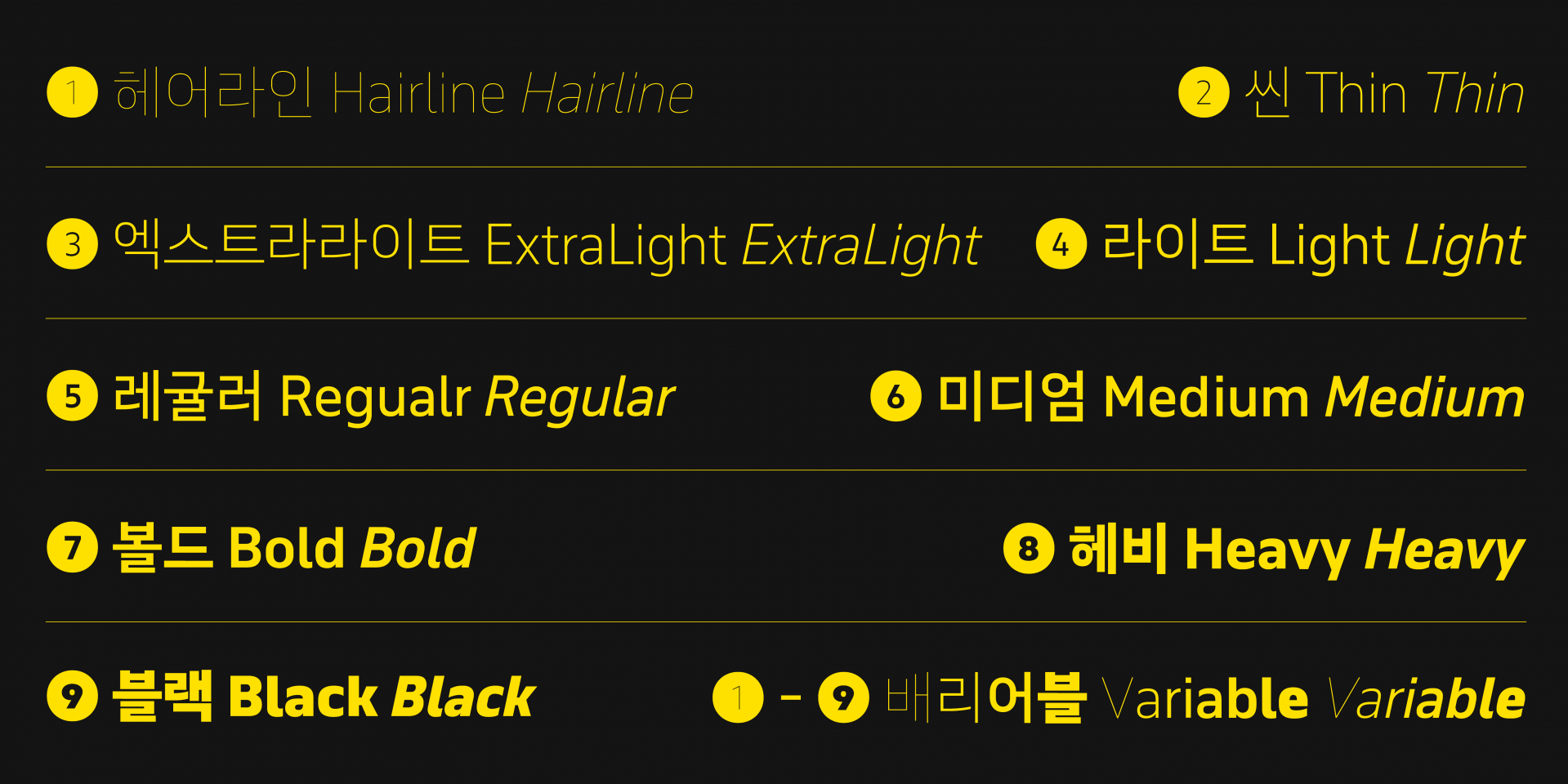
[Making font]세계 270곳에서 유창하게 대화할 수 있는 대가족
만나서 반갑습니다! 「SD 노벰버」
티포텍과의 새로운 협업, 「SD 노벰버」
산돌은 다년간 티포텍(Typotheque)과의 여러 협업 프로젝트를 진행해오며 완성도 있는 다국어 폰트 패밀리를 출시해왔습니다. 첫 협업 프로젝트였던 「Sandoll 그레타산스」*와 작년 4월에 출시된 「Sandoll 라바」는 출시된 이후로 사용자들의 많은 사랑을 받아온 폰트였어요. 이러한 글로벌 협업 프로젝트의 강점은 각 언어권의 글자를 각국의 전문가들이 다루기 때문에 완성도 높은 하나의 패밀리로 설계된다는 점입니다.
「November」는 티포텍에서 개발한 실용적이고 가독성이 높은 폰트 패밀리입니다. 도로 표지판이나 정보 전달 시스템을 위해 설계되어, 긴 텍스트에 사용하기 적합하고 작은 크기의 본문에도 사용하기 좋은 강점을 지니고 있죠. 이러한 목적 때문에  픽토그램과 같은 여러 정보성 딩뱃 글립들이 포함되어 있어요.
본격적인 협업 프로젝트를 시작하기 전, 티포텍의 디렉터 피터 빌락(Peter Biľak)과 「November」의 여러 가지 확장 가능성을 논의했습니다. 그 이유는 「November」는 마치 원석처럼 여러 스타일로 확장될 수 있는 가능성을 품고 있는 패밀리이기 때문이었어요.
「November」에서 획을 굴린 라운디드 버전의 「October」, 「November」의 가로 폭을 줄인 「November Compressed」와 「November Condensed」 등 다양한 스타일에 기본적으로 굵기 9종이 제공되니 모든 종 수를 가늠하면 정말 슈퍼 패밀리라고 부를 수 있을 정도의 대가족*임이 분명했습니다.
*폰트 패밀리는 하나의 폰트를 기준으로 다양한 변형이 있는 폰트 모음을 뜻합니다. 패밀리마다 구성은 조금씩 다르지만 얇은 웨이트의 라이트, 중간 웨이트의 레귤러, 굵은 웨이트의 볼드가 대표적입니다. 패밀리를 구성하는 폰트들은 전체를 관통하는 큰 컨셉은 유지한 채로 각각의 스타일을 가지고 있다는 맥락에서 폰트 패밀리를 지칭할 때 가족이라는 표현을 사용하고는 합니다.
물론 모든 스타일을 한글에 적용하기는 어렵겠지만, 이러한 매력적인 가능성들을 품은 채로 가장 기본이 되는 「November」의 한글 버전인 「SD 노벰버」의 작업을 시작하게 되었습니다.
다국어 프로젝트를 다루는 일
라틴 문자에 한글을 맞추는 일은 고려해야 할 점이 참 많습니다. 단순히 디자인을 일관적으로 맞추는 것을 떠나 한글의 물리적인 위치, 크기, 공간 등 패밀리의 성격에 따라서도 달라질 수 있는 부분들이 많거든요. 전혀 다른 나라에서 온 문자들은 각국의 역사적, 문화적 맥락을 품고 있어요. 때문에 「November」와 같은 인상으로 보일 수 있도록 하면서, 한국에서 통용되는 맥락에서 벗어나지 않도록 하는 것이 가장 중요한 지점이었습니다.
본격적인 작업을 시작하기 전, 「November」에 관한 모든 정보를 수집해서 분석하고 티포텍의 피터 빌락과 티포텍의 여러 협업 디자이너들과 함께 킥오프 미팅을 진행했습니다. 미팅에서  「November」 한글 보다 먼저 작업을 진행 중이던 「November」 가나, 「November」 한자를 직접 작업한 디자이너에게 다양한 내용을 공유 받을 수 있었어요.
흔히 CJK문자라고 불리는 동아시아 3개국(중국, 일본, 한국)의 문자는 다른 점도 많지만, 관계가 밀접하여 비슷한 맥락도 많습니다. 때문에 이 미팅을 통해 자국 문자의 맥락을 반영한 방식, 시각적 특징을 반영한 방식 등 「November」 한글 작업 방향성에 대한 여러 힌트를 얻을 수 있었어요.
킥오프 미팅에서 얻은 힌트들과 「November」 자료 분석을 토대로 용도(purpose), 시각적 범위(design), 인상(impression)이라는 세 개의 큰 주제를 설정해 「SD 노벰버」의 방향성을 확인하는 워크숍을 진행했습니다.
용도에선 「노벰버」가 실제로 사용될 매체와 환경에 대해 고민해 보고, 굵기별 적절한 용도를 설정했어요. 또한 한국에서 주로 사용되는 산세리프 폰트들을 찾아 한글의 너비감, 구조, 자소의 위치와 크기감 등 통용되는 특징들을 파악했습니다. 기민한 사용자들이 너무 놀라지 않을 정도의 시각적 범위를 지정하고, 「November」의 형태를 분석해 실제로 「노벰버」에 적용할 시각적 특징들을 찾아냈어요. 또한 한글 시안이 「November」와 비슷한 인상을 갖고 있는지 점검하기 위해 「November」에서 느껴지는 인상들을 추출했습니다.
이와 같이 주제별로 적절한 방향성을 설정하여 「November」의 시각적 특징들을 반영한 「노벰버」의 한글 시안 작업을 시작했습니다.
「SD 노벰버」 제안서 중 일부 이미지 - 키워드 추출
산돌에서 발견한 「November」의 두드러지는 시각적 특징은 ① 수직·수평의 획 끝 디자인, ② 트랙 형태의 'O' 디자인, ③ 비교적 좁은 너비감, 크게 이 세 가지였는데요. 라틴의 디자인적 특징을 한글에 100% 반영하는 것은 서로 다른 문자의 맥락으로 인해 불가능에 가까운 일입니다. 하지만 이를 적절히 반영하는 것이 바로 폰트 디자이너의 몫이죠.
① 수직·수평의 획 끝 디자인
「November」는 터미널(Terminal), 즉 모든 획 끝이 수직·수평으로 잘리는 시각적 특징을 가지고 있습니다. 이로 인해 모든 속공간이 열린 형태가 되며, 글자 여백(Sidebearing)이 깨끗해져 어떠한 매체나 크기로 사용하더라도 높은 가독성을 유지하는 데 영향을 줍니다.
이러한 특징은 라틴에선 충분히 통용되고 있는 디자인이지만 한글에서는 일반적이지 않은 특징인데요. 보통 ‘ㅅ, ㅈ, ㅊ’과 같은 삐침류는 획의 흐름에 따라 사선으로 마무리되는 것이 자연스럽기 때문이에요. 하지만 최대한 이를 반영하기 위해 여러 시안 테스트를 거쳤고, 삐침류를 좌우 대칭의 갈래 방식으로 디자인하여 획 끝이 수직으로 끝나도 어색하지 않도록 설계하였습니다. 이 획 끝 디자인은 기계적인 인상을 만들어내지만, 곡선 부분을 부드럽게 다듬어 그러한 인상이 과해지지는 않도록 했어요. 본문이라는 용도에도 적절히 스며들어야 했기 때문이죠.
사실 이러한 터미널 표현은 라틴에는 가독성에 긍정적인 효과가 있지만, 한글에서는 단순히 시각적 특징으로 반영됩니다. 때문에 「노벰버」는 가독성을 위해 낱글자 안에서의 획을 최대한 깔끔하게 붙이거나 떨어뜨리는 등의 공간 조절과 굵기 조절을 통해 보완했습니다.
「SD 노벰버」 제안서 중 일부 이미지 - 디자인 시안
② 트랙 형태의 'O' 디자인
또 다른 시각적 특징인 트랙 형태의 ‘O'를 한글에 반영하는 부분도 비슷한 어려움을 겪었습니다. 라틴 ‘O’에 비해 한글의 ‘ㅇ’과 ‘ㅎ’은 가로로 좁아진다던가, 세로로 좁아지는 등의 변수 폭이 크기 때문인데요. 이 부분은 정말 패스와 점을 섬세하게 다루는 방법밖엔 없어서 많은 시간을 들여 보정했습니다. 높이가 줄어들수록 세로획의 직선 표현이 두드러지지 않도록 조정하는 것이 관건이었습니다.
③ 비교적 좁은 너비감
마지막으론 너비감입니다. 한국에서 주로 사용되는 고딕류 레퍼런스들과 비교했을 때 「November」는 일관적인 너비감을 갖고, 균일하고 촘촘해 보이는 인상이 듭니다. 때문에 「노벰버」의 한글 너비 설정도 이와 같은 느낌을 살리고자 했어요. 추후 앞서 언급했던 「November Compressed」와 「November Condensed」로 확장되는 것까지 고려해 최대 너비가 너무 좁아지지 않도록 적절한 범위 안에서 한글의 너비를 설정했습니다.
추가로 「노벰버」를 제작하면서 고민되었던 포인트 중 하나는 ‘한글과 라틴, 그리고 라틴에 맞춰진 문장부호를 어떻게 조정할 것인가’에 관한 부분이었습니다. 「노벰버」는 산돌에서 세 번째로 진행하는 다국어 협업 프로젝트였기 때문에 앞선 프로젝트인 「Sandoll 그레타산스」와 「Sandoll 라바」를 레퍼런스로 참고할 수 있었어요.
한글과 라틴은 각각 따르는 기준선이 다릅니다. 특히 라틴의 경우 그 기준선이 한글에 비해 확고합니다. 라틴의 문장부호도 베이스라인(Baseline)을 기준으로 엑스 하이트(x-height), 캡 하이트(Cap Height)에 맞춰 자로 잰 듯 정렬되어 있죠. 극단적 정렬 덕후라면 반색할지도 모르겠습니다.
그에 반해서 한글의 문장부호는 라틴과는 다르게 눈에 확연히 보이는 기준선이 존재하지 않습니다. 폰트마다 다르기도 하고 비슷하기도 한 문장부호의 위치. 현대 한글에서 사용되고 있는 대부분의 문장부호의 기원이 한글 태생이 아니기 때문일까요? 기준선에서 벗어나 비교적 자유로워졌기 때문에 폰트 디자이너는 깊은 고민에 빠집니다.
라틴과 한글의 기준선 차이
「그레타산스」와 「라바」는 기존 라틴의 문장부호에서 한글에 알맞도록 형태 자체를 변형했습니다. 게다가 「라바」는 한글과 함께 많이 쓰이는 문장부호를 따로 디자인하여 어도비 프로그램에서 사용할 수 있는 Locl기능*을 추가하기도 한 폰트입니다.
하지만 「노벰버」는 여러 확장 가능성을 가지고 있었고, 범용성을 고려하여 최대한 부가적인 기능을 삭제하고자 했습니다. 때문에 한글과 자주 쓰는 문장부호의 경우는 한글에 맞게 길이감과 위치를 재조정하였고, 라틴과 숫자와 많이 사용되는 문장부호들은 최대한 그대로 사용했어요. 한글의 위치를 캡 하이트에 맞춰서 작업했기 때문에 이러한 방식이 어색하지 않을 수 있었습니다. 다국어 프로젝트는 디자이너가 어떤 부분을 고려하는가에 따라, 길이 여러 갈래로 나누어지게 되는, 정답이 없는 재미난 프로젝트라고 생각이 들어요.
농부와 요리사 같은 사이
농작물을 잘 가꿔내는 것은 농부가, 그 농작물을 하나의 멋진 요리로 만드는 것은 요리사의 역할입니다. 이와 같이 폰트 디자이너와 여러 분야의 디자이너 간의 관계는 뗄 수 없는 양방향적인 사이입니다. 아마 대부분의 폰트 디자이너는 폰트 출시 후 첫 사용 사례를 발견하는 순간을 기억하고 있을지도 모릅니다. 그만큼 실제로 사용된 사례를 수집하는 일은 폰트 디자이너에게 폰트를 만드는 일만큼 중요합니다. 때로는 예상치 못한 환경에서 색다르게 쓰인 사용 사례를 보고 인사이트를 얻는 경우도 있습니다.